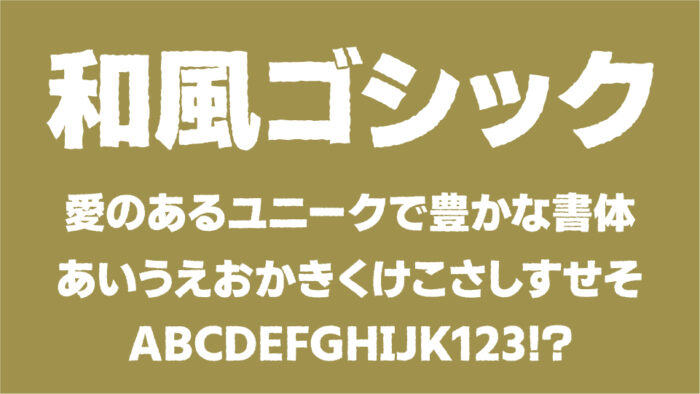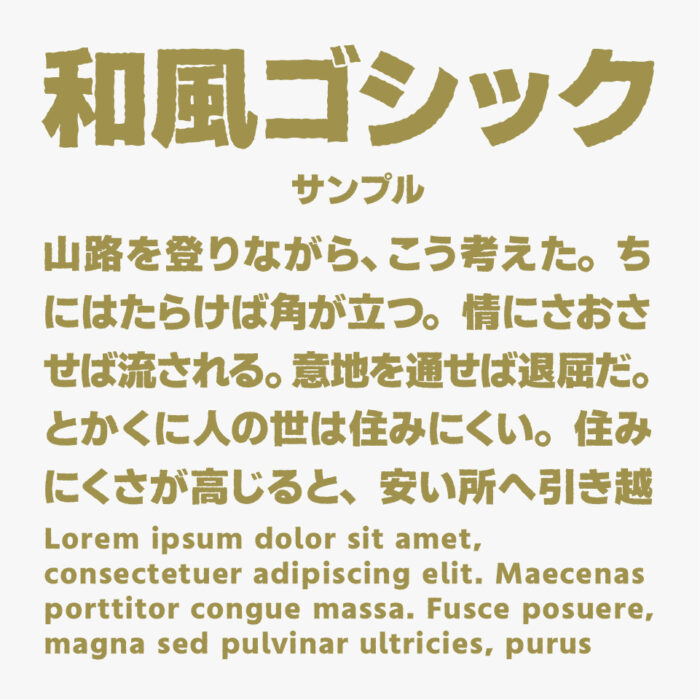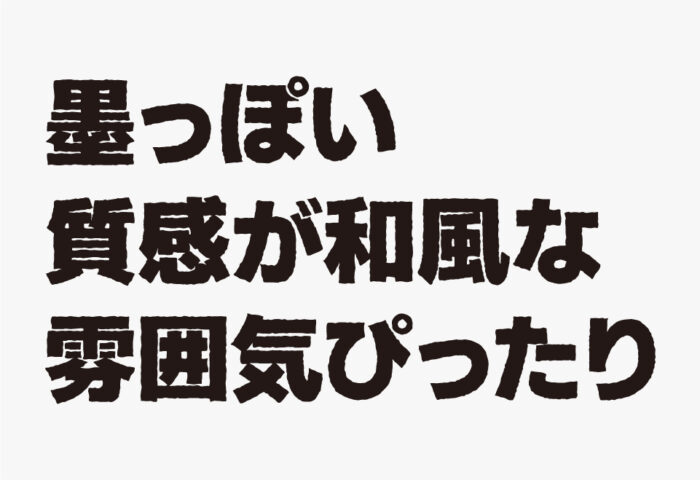
和風ゴシック
和風ゴシックフォントは、「源暎エムゴ」フォントをベースとして、ラフ加工を施した角ゴシックフォントです。
文字の輪郭にジャギジャギとしたラフ加工が施されていることにより、滲みやかすれ感のある質感になり、和の情緒を漂わせるゴシック体フォントとなっています。
見出しやタイトルなどの比較的大きいサイズで使用するとラフの質感がしっかり見えて、墨が滲んだような質感を感じれて、和風の雰囲気にぴったりなフォントです。